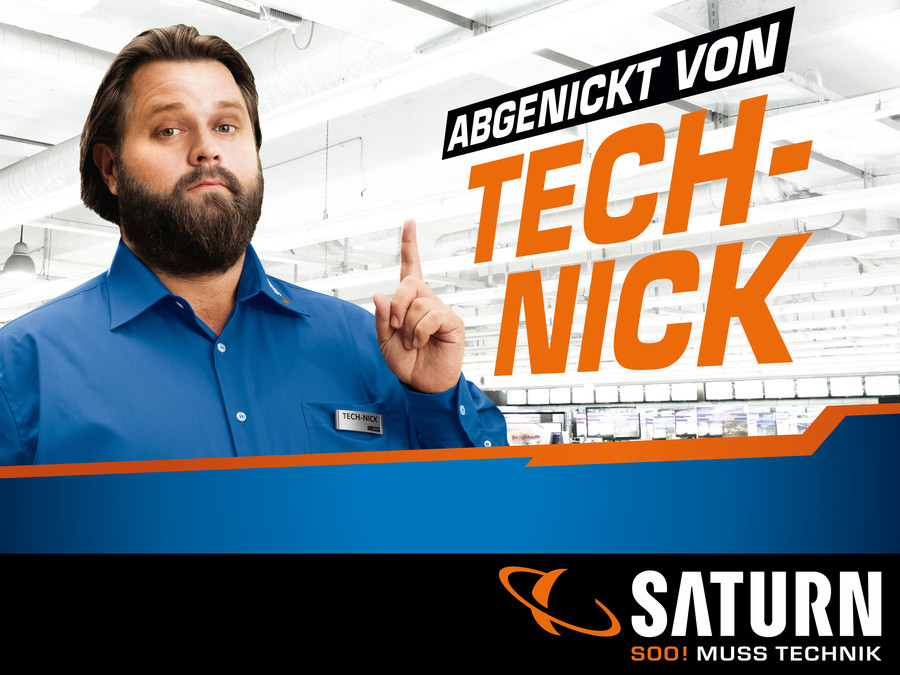
Schriftart Gesucht- Saturn Spot
Ihr kennt doch bestimmt alle den "BEI TECHNIKFRAGEN TECH-NICK FRAGEN" Spot.
Weiß vielleich jemand von euch, welche Schriftart das ist, oder welche ihr ähnlich sieht? Ich kenne die, aber mir fällt der Name nicht ein. Tech-Nick.jpg
Spontan würde mir die Eurostile einfallen. Es gibt aber auch kostenlose, ähnlich aussehende Ersatzschriften wie Waukegan.
Impact ist es jedenfalls nicht. Siehe meine Vergleichsgrafik.